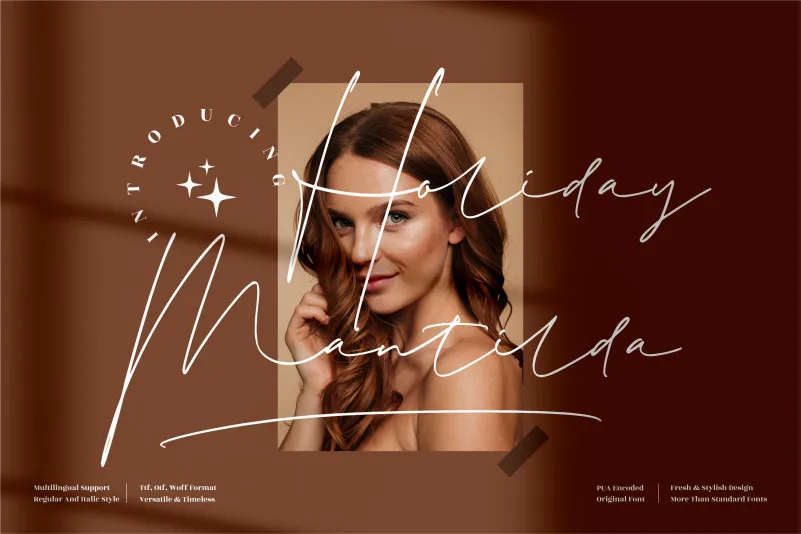
A “Holiday Mantilda Font” é uma opção perfeita para estilos decorativos e elegantes que valorizam a escrita à mão. Desenvolvida pelo designer perspectype, essa fonte de grife é ideal para projetos como logotipos, design de embalagens, produtos em estoque, mugs, cartões de convite ou até mesmo retratos, carteiras personalizadas e selinhos de aniversário. Seja você um criador de logos profissional ou alguém buscando dar vida a seus projetos pessoais com um toque de elegância e sofisticação, “Holiday Mantilda Font” é perfeitamente adaptada para atender às suas necessidades. Com sua variedade de linhas e tamanhos, essa fonte oferece uma maneira única de incorporar detalhes únicos a seus projetos, tornando-os ainda mais memoráveis. Seja em um evento especial ou em um projeto pessoal que você está desenvolvendo, este é o elemento de design perfeito para atingir seu objetivo com sucesso.